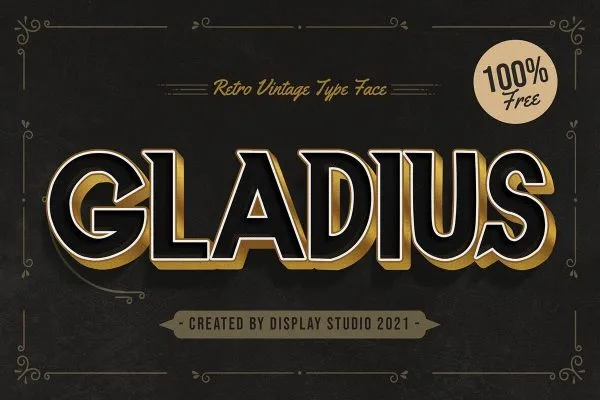
Gladius Font – Fonte Grátis
Gladius Font
A Gladius Font é uma nova adição à categoria dos Fonts Display, criada pela Display Studio. Especificamente desenvolvida para quem busca uma tipografia afiada e limpa, essa font foi projetada para atender a diversos usos, desde criação de marcas de marca até design de cartões de convite ou qualquer projeto que deseje um destaque visual impressionante. Com sua natureza bold e assertiva, a Gladius é perfeita para quem procura uma tipografia capaz de destacar-se em qualquer ambiente. Além disso, a fonte possui uma funcionalidade multilíngue e variedade de estilos que permite adaptá-la ao seu projeto específico, tornando-a ainda mais versátil. Para designers atentos à elegância, essa font é definitivamente uma opção a ser considerada para suas próximas criações.